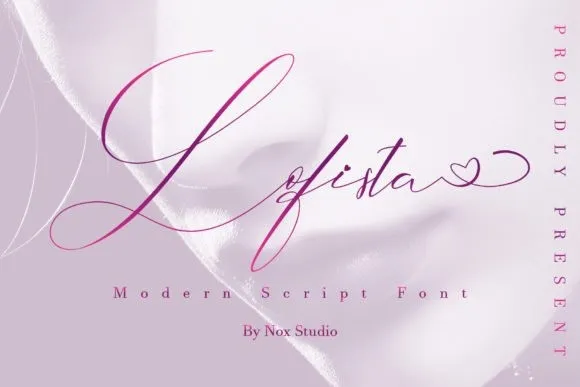
Esta fonte script Lofista é uma criação intrigante da 99designs, desenhada para atrair olhares atentos com sua linhas não convencionais e estilo moderno e feminino. Com seu traçado meticuloso e detalhes cuidadosamente elaborados, ela se destaca como um ativo valioso em qualquer coleção de fontes. O fato de ser PUA (Unicode) encoded é particularmente atraente, permitindo que você navegue com facilidade entre todos os símbolos e ganchos da fonte, aumentando seu potencial ainda mais para complementar qualquer projeto gráfico. Seja em um layout editorial ou uma obra de arte digital, Lofista oferece uma opção única e vibrante que certamente irá enriquecer seu trabalho.